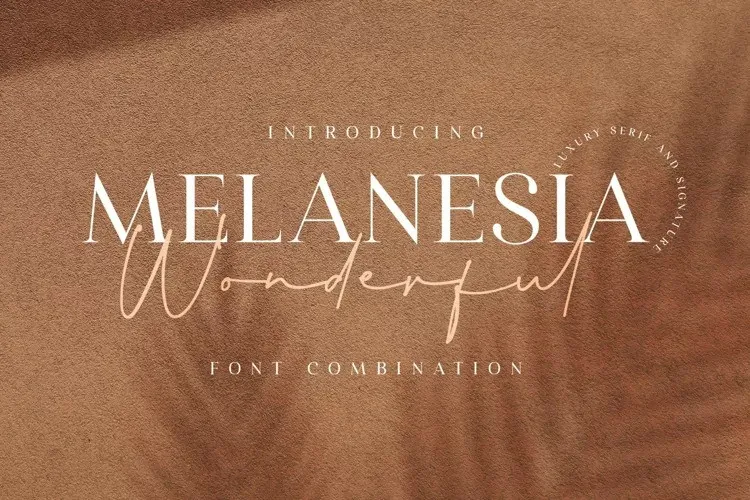
Wonderful Melanesia Font – Download Grátis
A ‘Wonderful Melanesia Font’ é uma elegante escolha para qualquer projeto que busque adicionar um toque atraente ao design. Esta fonte script foi cuidadosamente criada, atentando a cada detalhe dos traços das letras. Ela se destaca como uma combinação perfeita de charme e sofisticação, ideal tanto para projetos modernos quanto para aqueles que valorizam o minimalismo elegante. Perfeito para adicionar um toque especial em cartazes, logotipos ou qualquer outro tipo de design gráfico, esta fonte oferece a oportunidade de criar uma impressão chamativa e única. Ela é perfeita para os designers buscando incorporar um ar delicado no trabalho, seja em torno de elementos naturais ou em designs urbanos minimalistas. Com o ‘Wonderful Melanesia Font’, você pode certificar-se que seu design não apenas está funcionalmente correto, mas também possui uma sensação atraente e sofisticada. Ideal tanto para projetos pessoais quanto profissionais, esta fonte é uma ótima escolha para quem busca um complemento perfeito para qualquer projeto de design gráfico.